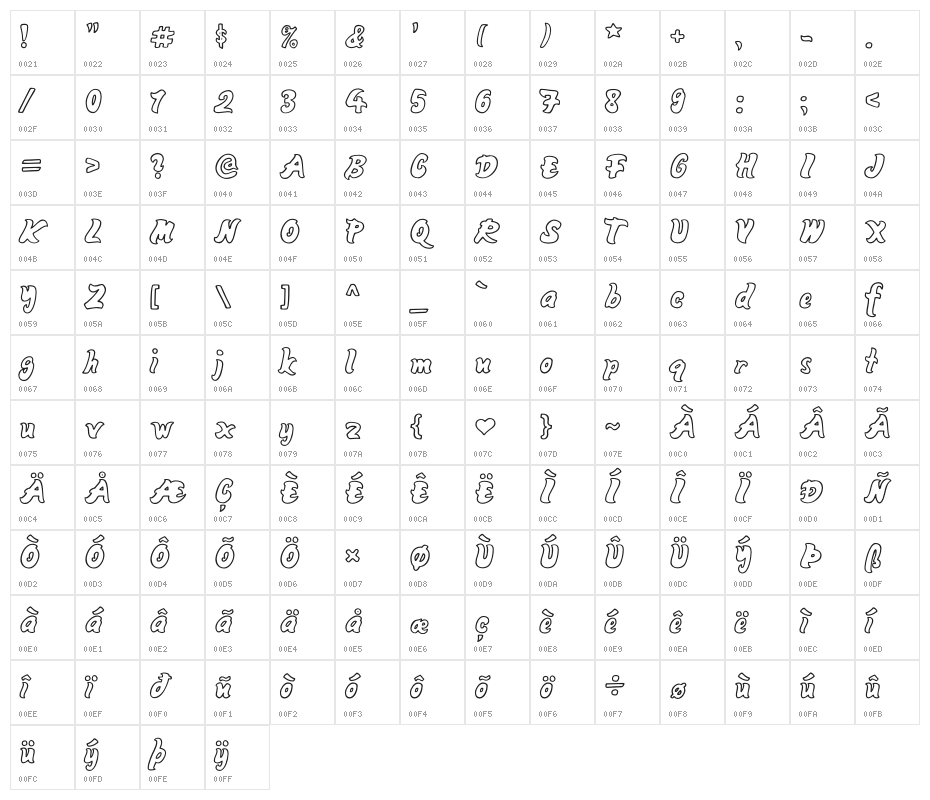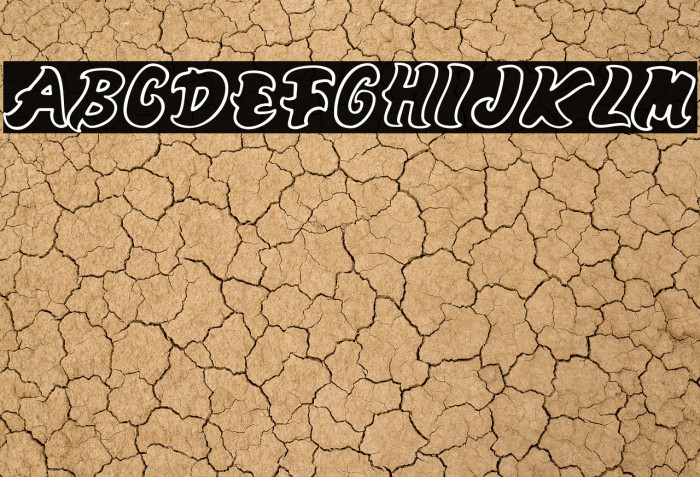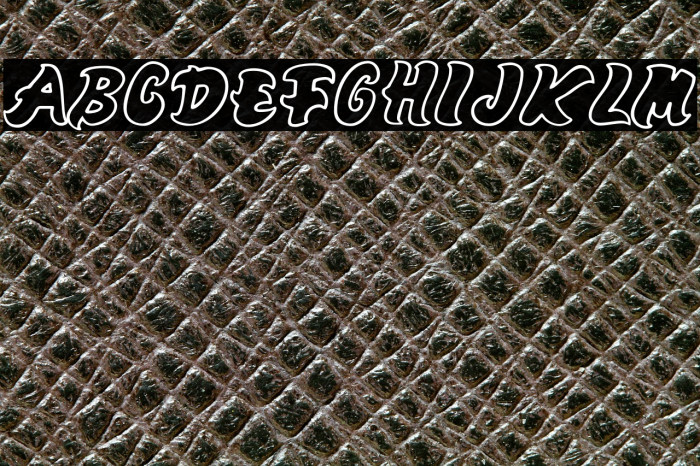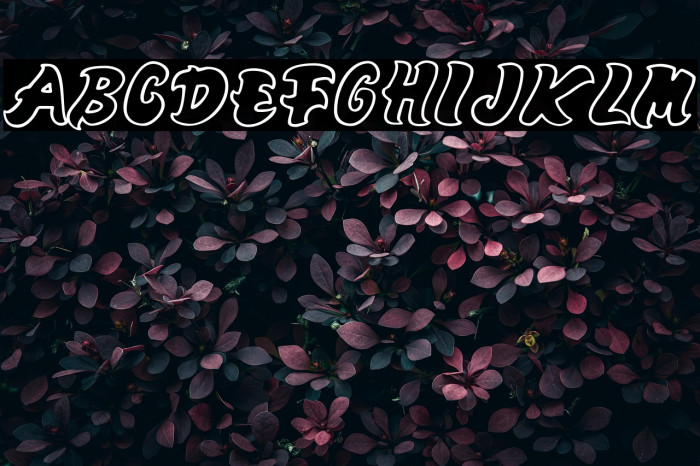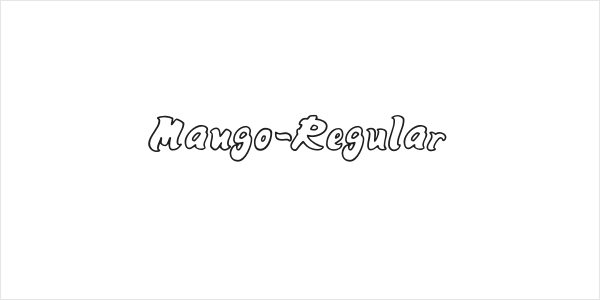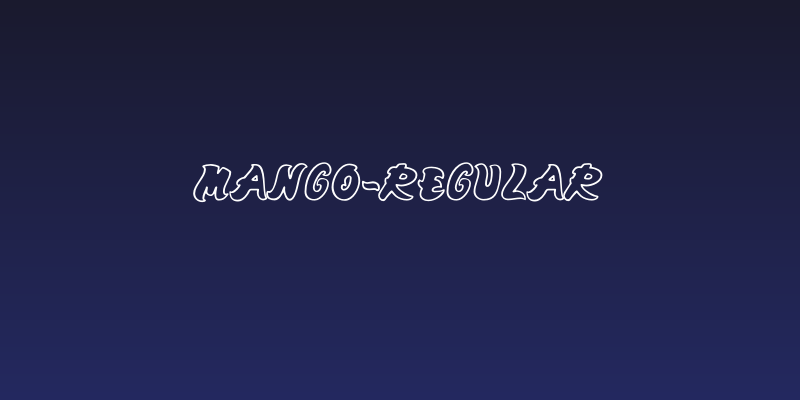
Mango-Regular Font
| Gesamtstil | Playful, Whimsical |
| Vorgeschlagene Projekte | Ideal for children's books, comic strips, playful branding, party invitations, and creative posters. |